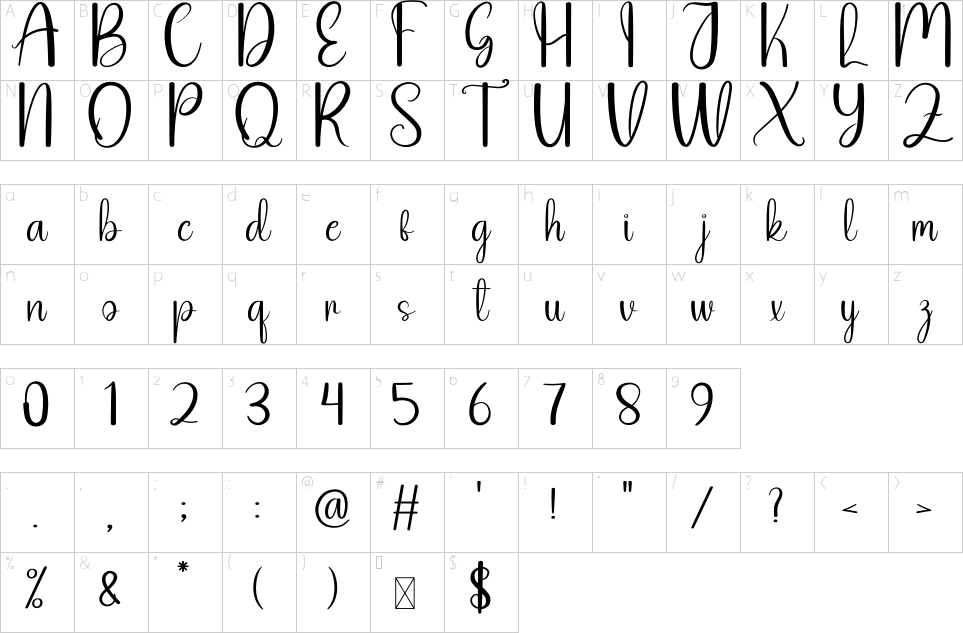
Descubra a essência do estilo casual e descontraído com Daddy Font. Esta elegante e versátil fonte foi criada por William Jhordy e destaca-se pela sua simplicidade, que faz dela uma escolha ideal para qualquer projeto. Seja você designer, editor de texto ou profissional de marketing, a Daddy Font é perfeita para adicionar um toque pessoal a suas criações digitais. Descubra o poder da autenticidade através desta fonte criada para quem busca algo além da superficialidade, mas que mantém um grau de sofisticação inerente às criações digitais atuais. A Daddy Font é uma escolha ótima para aqueles que valorizam a integridade e o encanto do design no mundo digital.